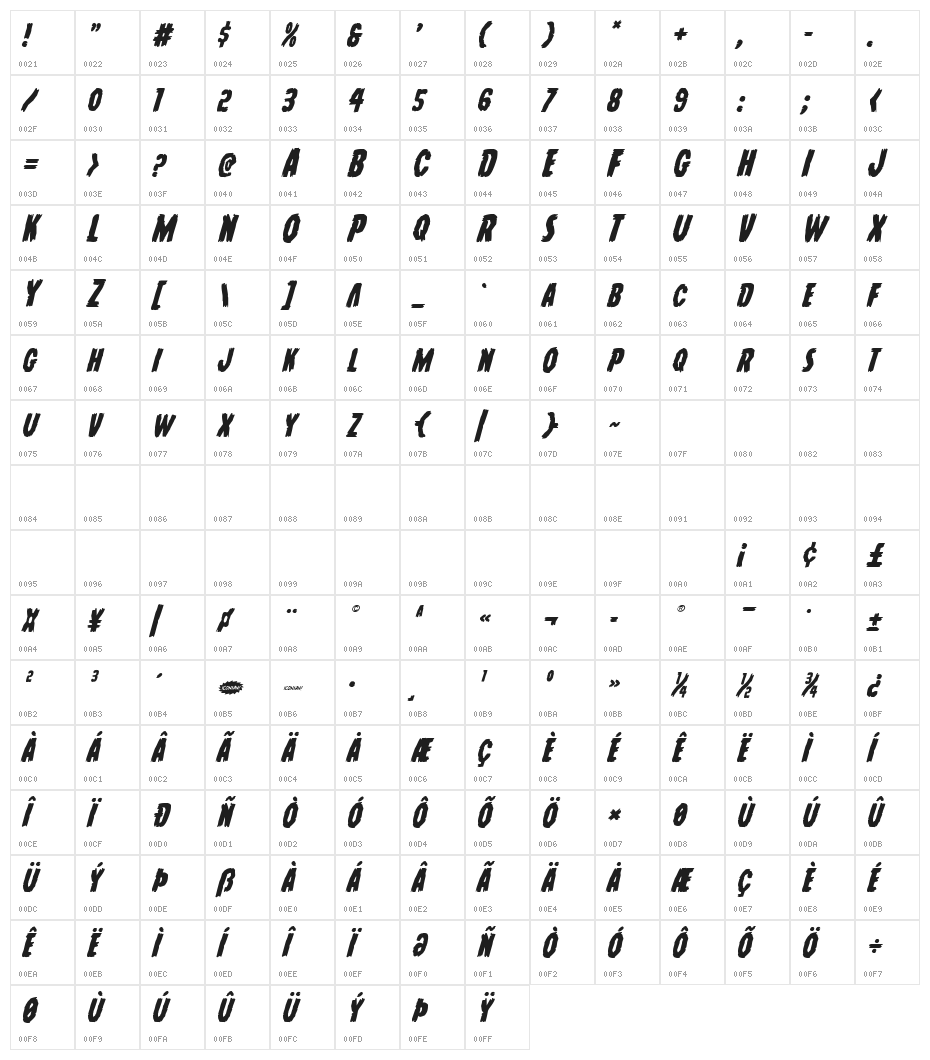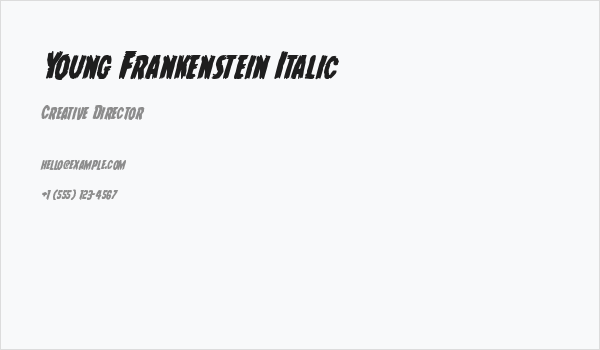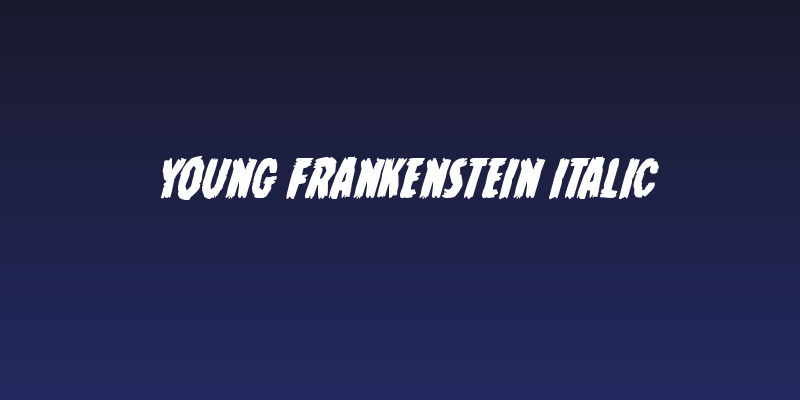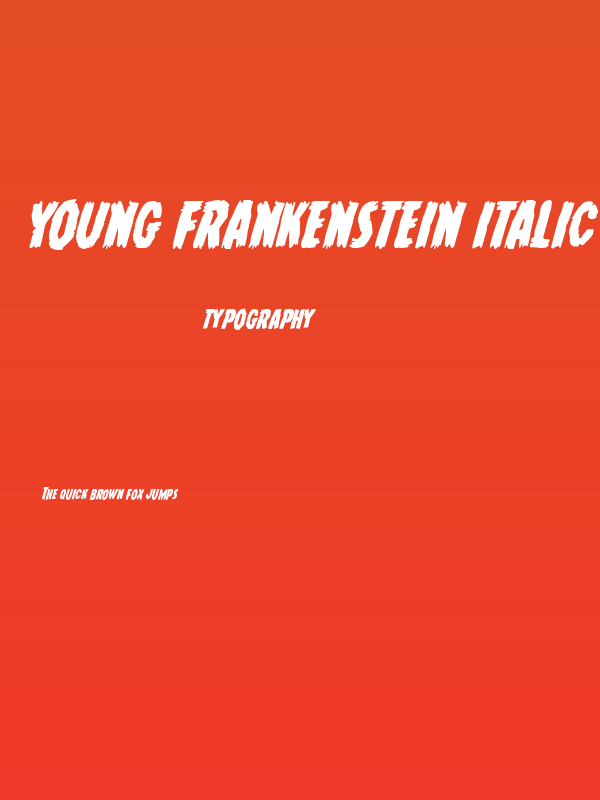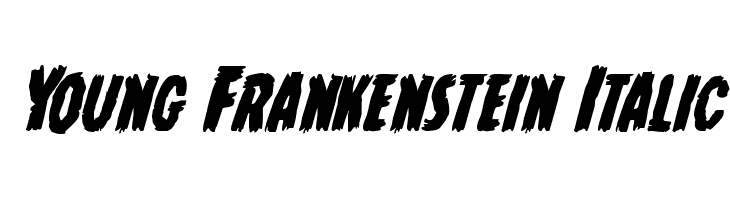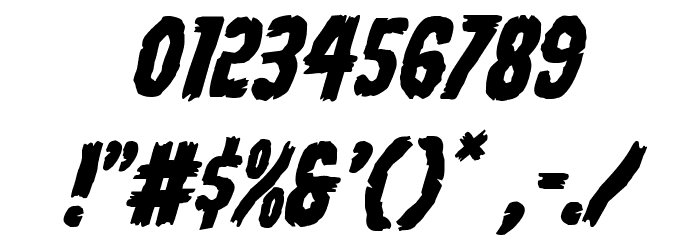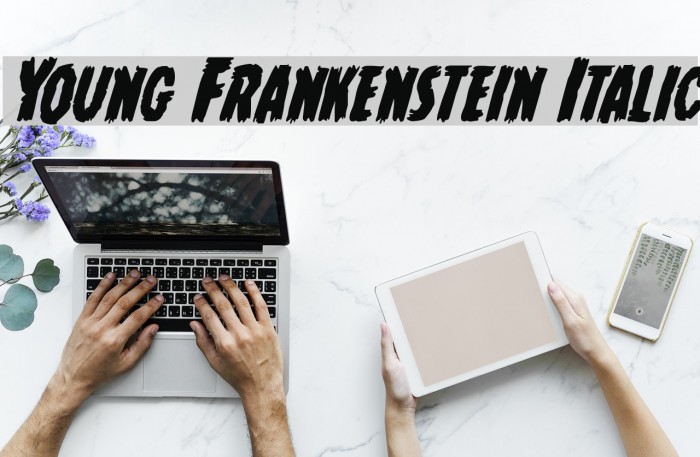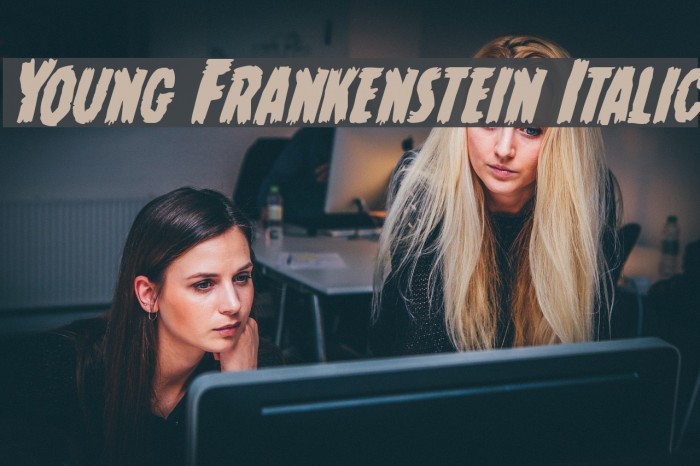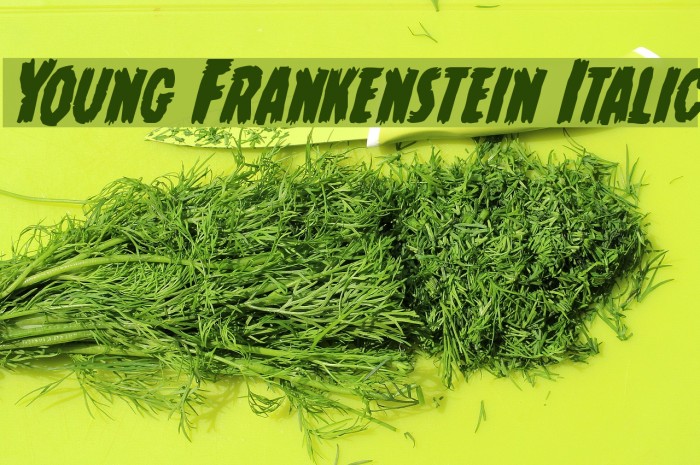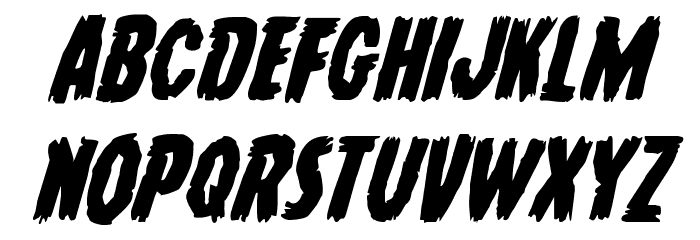
Young Frankenstein Italic Font
| Style général | Dramatic, Energetic, Expressive |
| Cas d'utilisation | Headlines, Posters, Themed Events |
| Projets proposés | Perfect for movie posters, horror-themed events, Halloween invitations, or any project needing a bold, eye-catching typeface. |